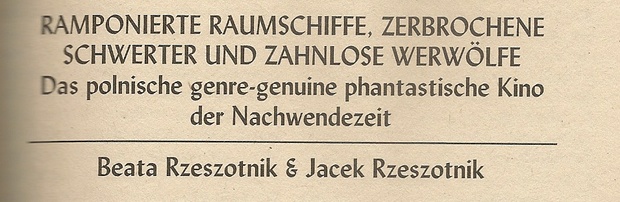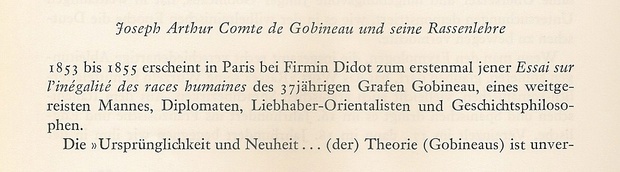
Benötige Hilfe, zwei Buchfonts zu identifizieren
Zwei Fonts sind mir in Büchern jeweils aufgefallen. Im Impressum war leider nichts angegeben. Hat jemand Rat?
A)
B)
Aus welchem Jahr sind die beiden Bücher?
Das obere Beispiel scheint eine Garamond zu sein, das untere ist die Lisbon.
Bei A müßte es sich um die Linotype Janson auf der Linotype-Setzmaschine handeln.
Nicht digital verfügbar.
Bei B um die Lydian von Warren Chappell, digital bei Bitstream vorhanden
Doch. Zumindest das R unterscheidet sich:
Die Lydian scheint mir auch eine Kleinigkeit schmäler zu sein, das ist aber nur schnell drübergeschaut.
Ich hab sie mit dem Original verglichen: